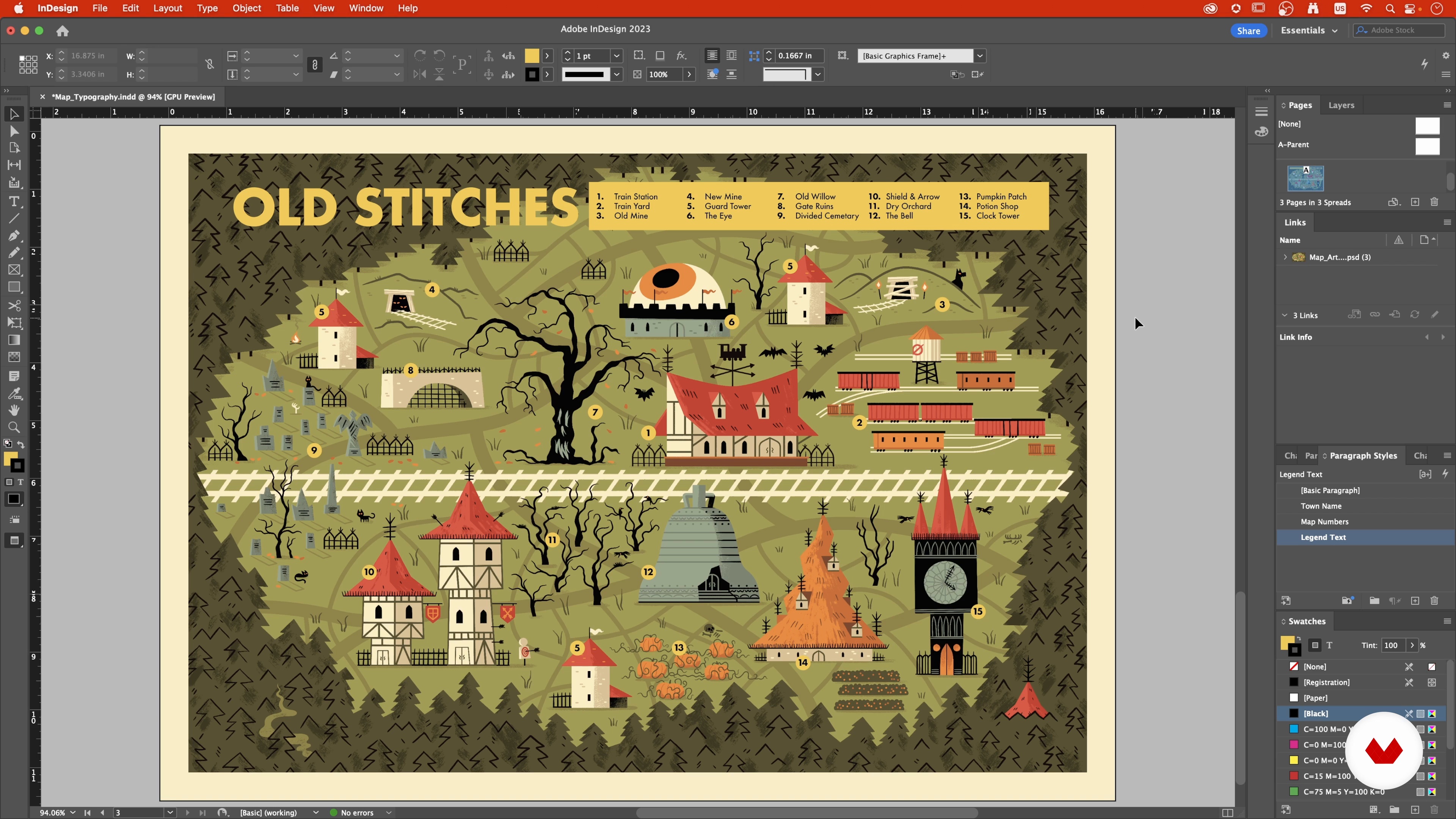
“La plus grande suggestion que j'ai est de laisser l'œuvre d'art briller. Une police simple peut fonctionner avec presque toutes les illustrations. Assurez-vous simplement que tout est assez grand et assez clair pour être lu. Continuez également à travailler avec l'unité (polices similaires), l'équilibre (grilles) et le contraste (sur le fond, en taille, etc.). ”
Dans cette leçon, Andrew Kolb aborde le sujet : Typographie 2, qui fait partie du cours Domestika en ligne : Cartes créatives pour jeux : illustrez un monde imaginaire. Créez des pièces cartographiques pleines de détails.
“Alors. avec cette numérotation faite. créons une légende. Parlons de la manière dont nous allons aborder Je vais commencer à nommer ces lieux. un par un. pour plus de clarté. et juste passer de l'un à l'autre. Il y a 15. J'essaie de garder les choses aussi simples que possible en nommant les lieux. J'essaie de rendre cela évident que possible. J'apprécie vraiment les écrivains de fantasy ou les concepteurs de jeux qui créent un grand nombre de traditions ou de secrets fabuleux. Mais je ne pense pas que cela soit représentatif de la réalité. Pensez à l'Amérique du Nord. aux Montagnes Rocheus...”